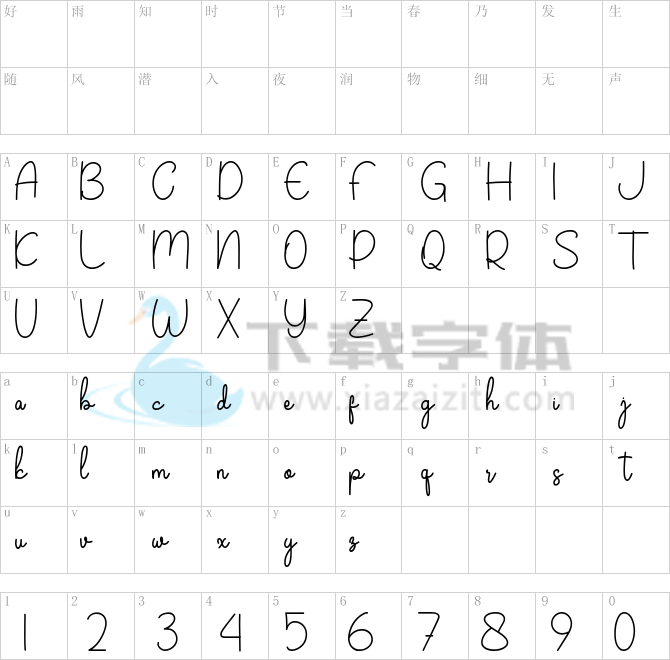
Aghellay.ttf字体下载
Aghellay.ttf字体下载,这款字体结构工整、笔画清晰,兼顾美观与易读性,适用于标题、正文、海报、包装、LOGO 等多种场景。字形优雅稳定,风格百搭耐看,适配日常排版与创意设计,让文字呈现更舒适、更具质感。Aghellay.ttf字体下载一笔一画,皆是细节,以均衡的比例、流畅的线条打造舒适视觉体验,字形端正大气,风格简约现代。无论是商业设计、品牌宣传还是日常排版,都能轻松驾驭,让文字更有格调与力量。Aghellay.ttf字体下载字体下载。